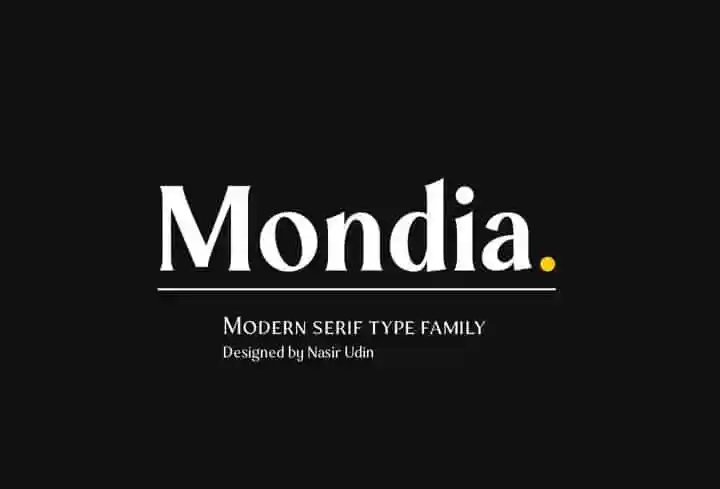
Mondia Serif Font – Download Grátis
A Mondia Serif Font é uma nova tipografia serifada criada pelo designer Nasir Udin. Este novo lançamento para a categoria das fonts serifadas é perfeito para seus próximos projetos de marca, ideal para empresas atemporais e modernas. Com alto contraste entre as letras e um x-height significativo, essa fonte traz elegância aos seus materiais de marca sem perder legibilidade. Suas linhas sólidas combinam com estilos tradicionais enquanto mantêm uma aparência contemporânea, tornando-a ideal para aplicações como cartões de visita, identidade visual ou qualquer projeto que exija um tom sofisticado e confiável. Não importa o estilo da sua marca, a Mondia Serif está aqui para complementá-la em qualquer projeto que você possa imaginar.